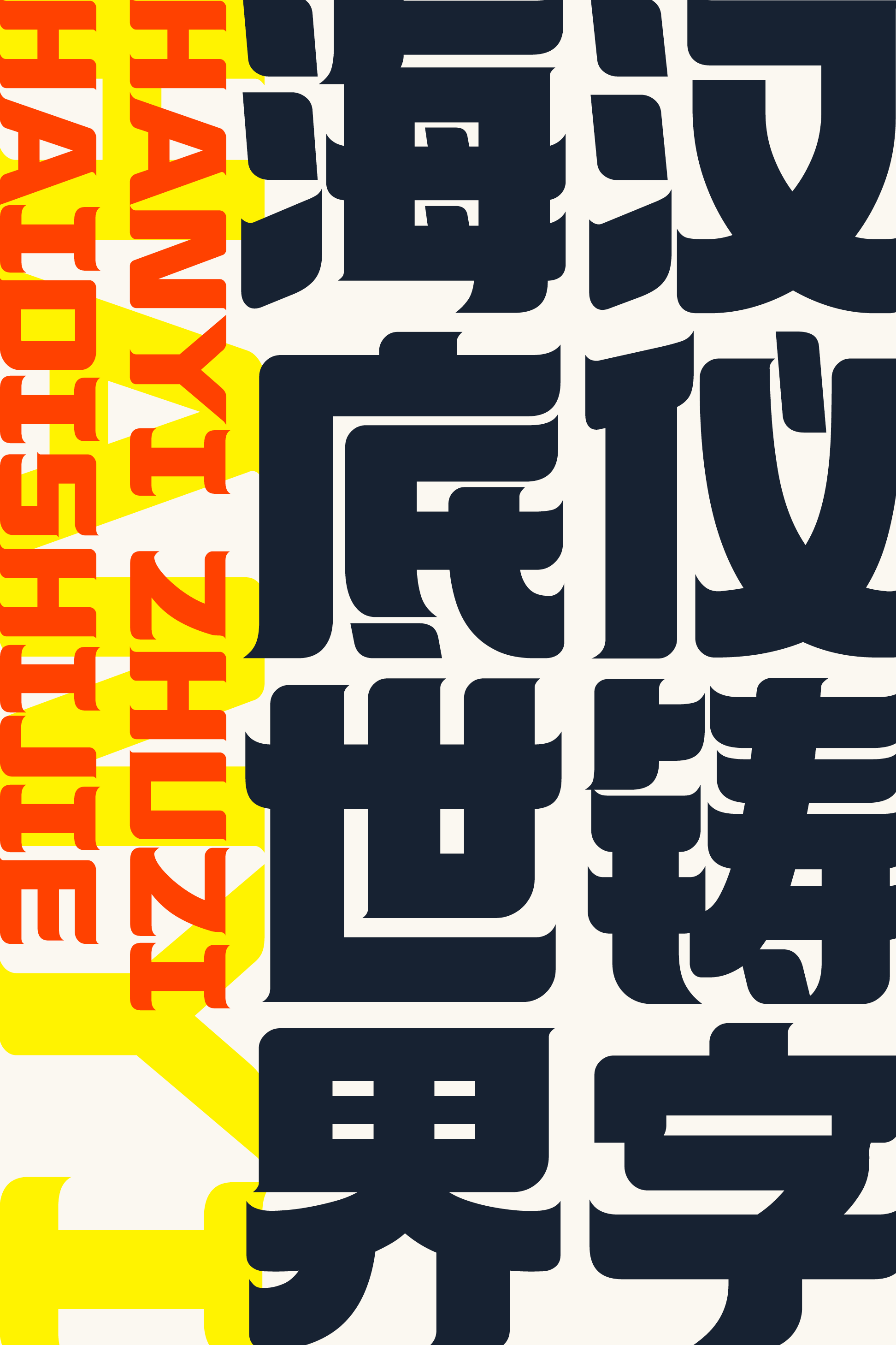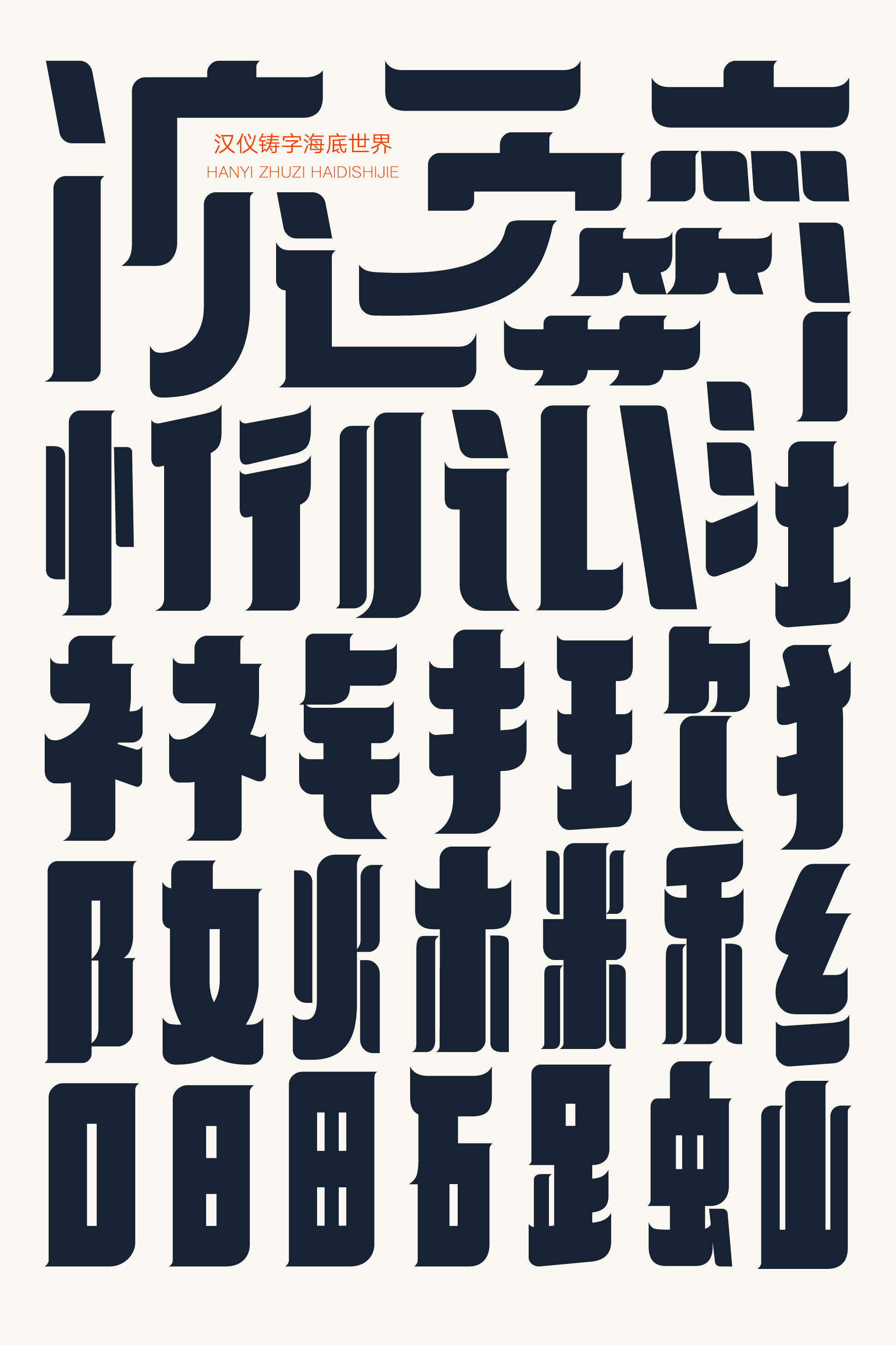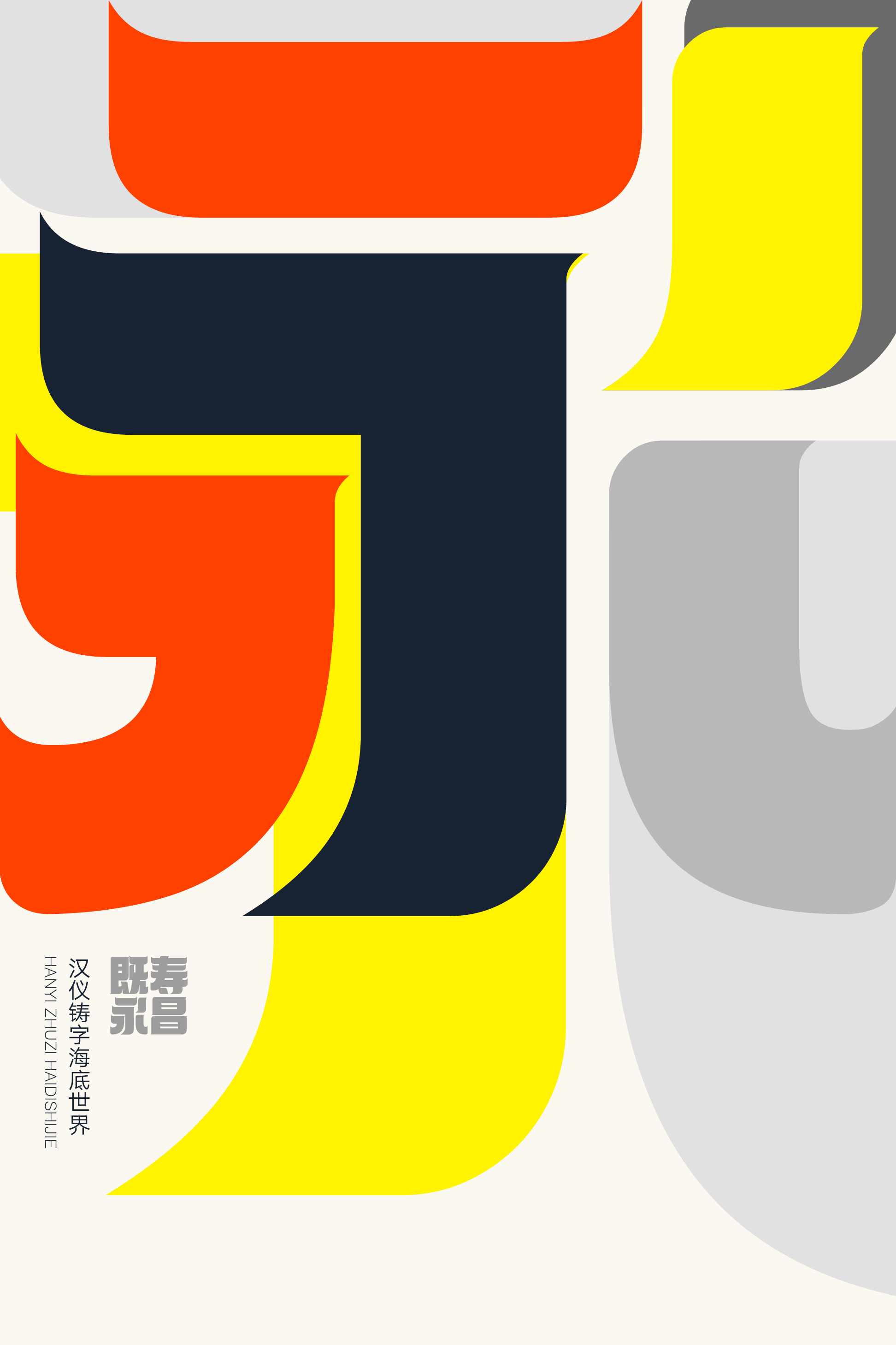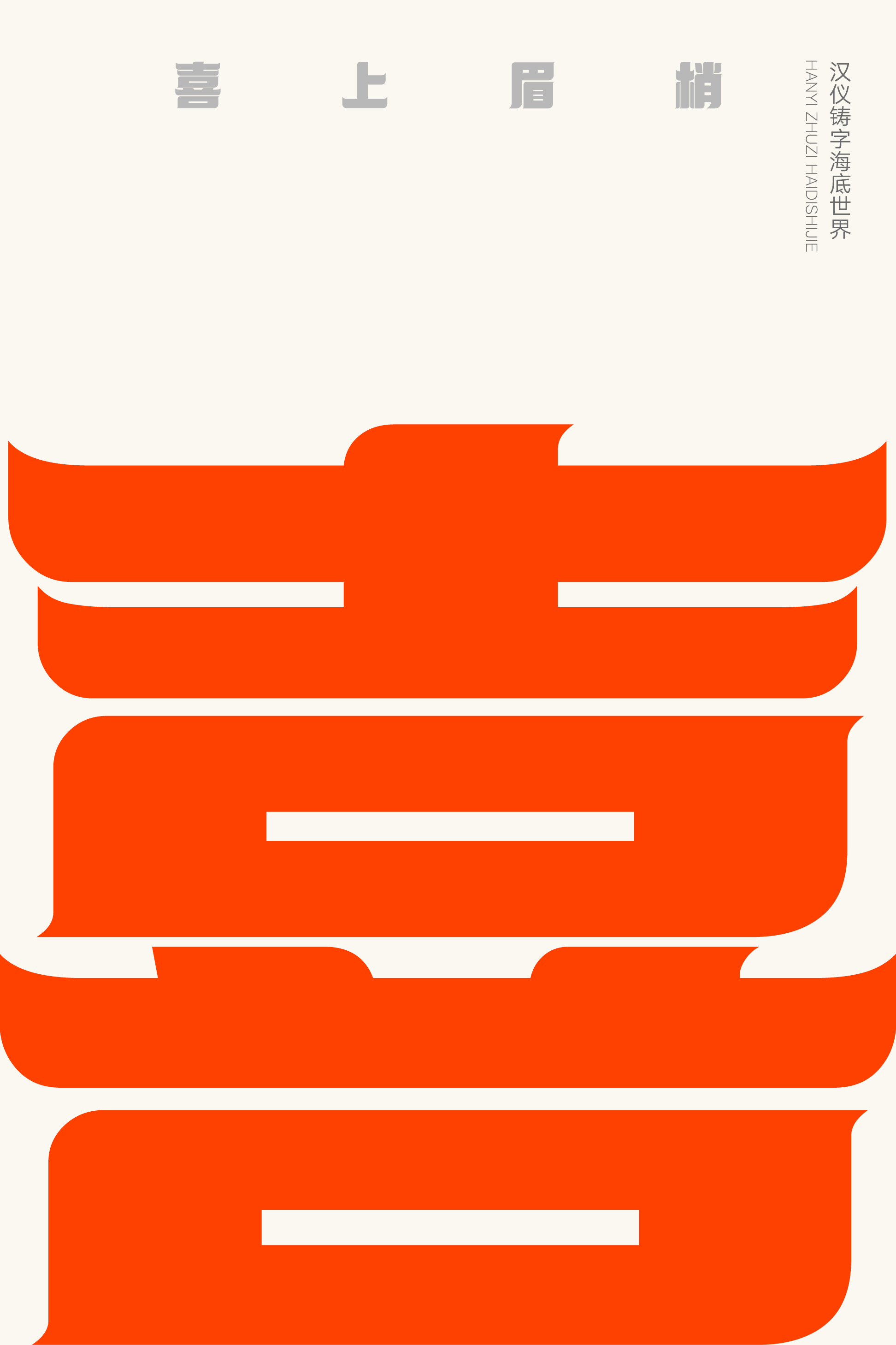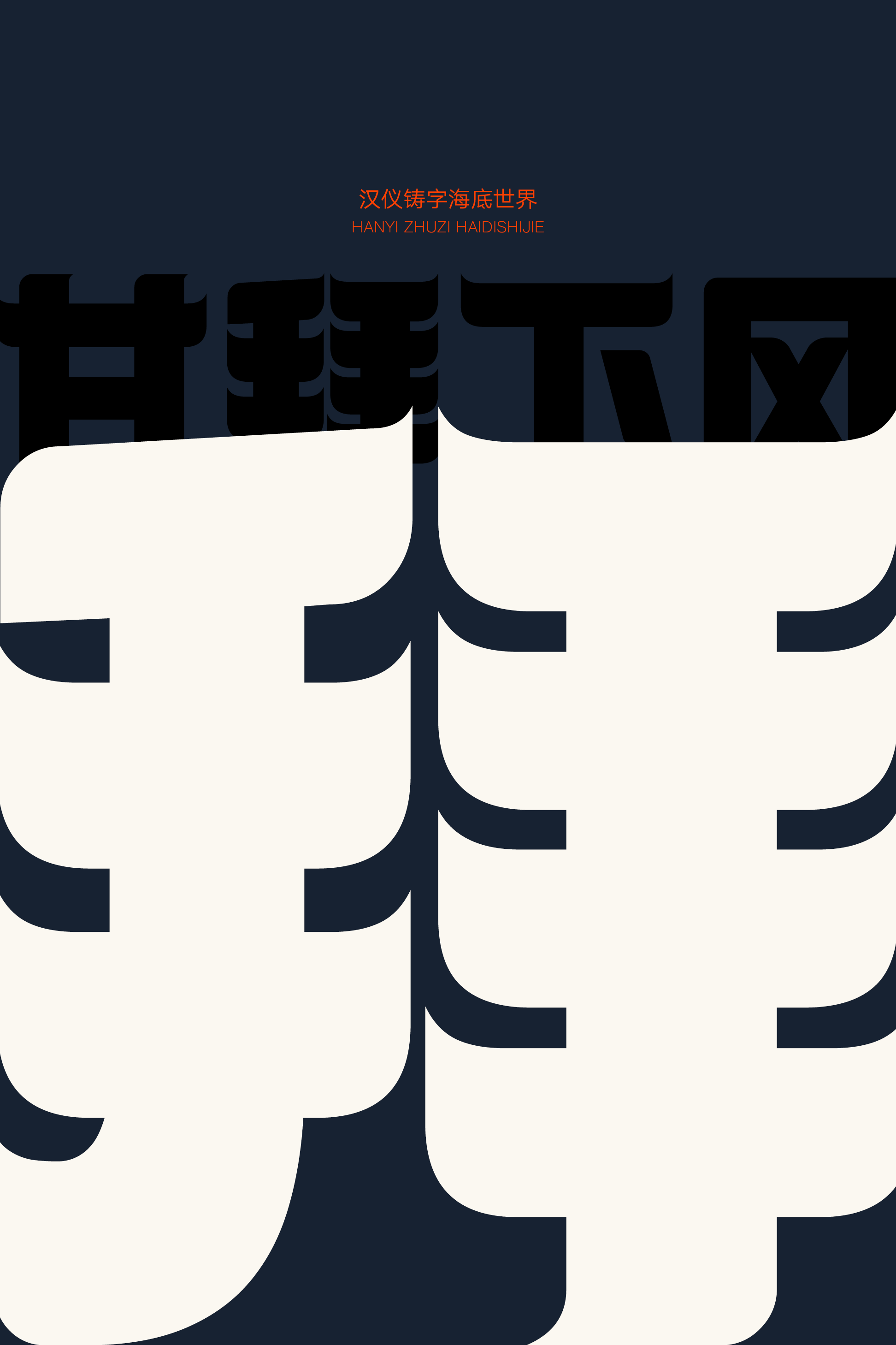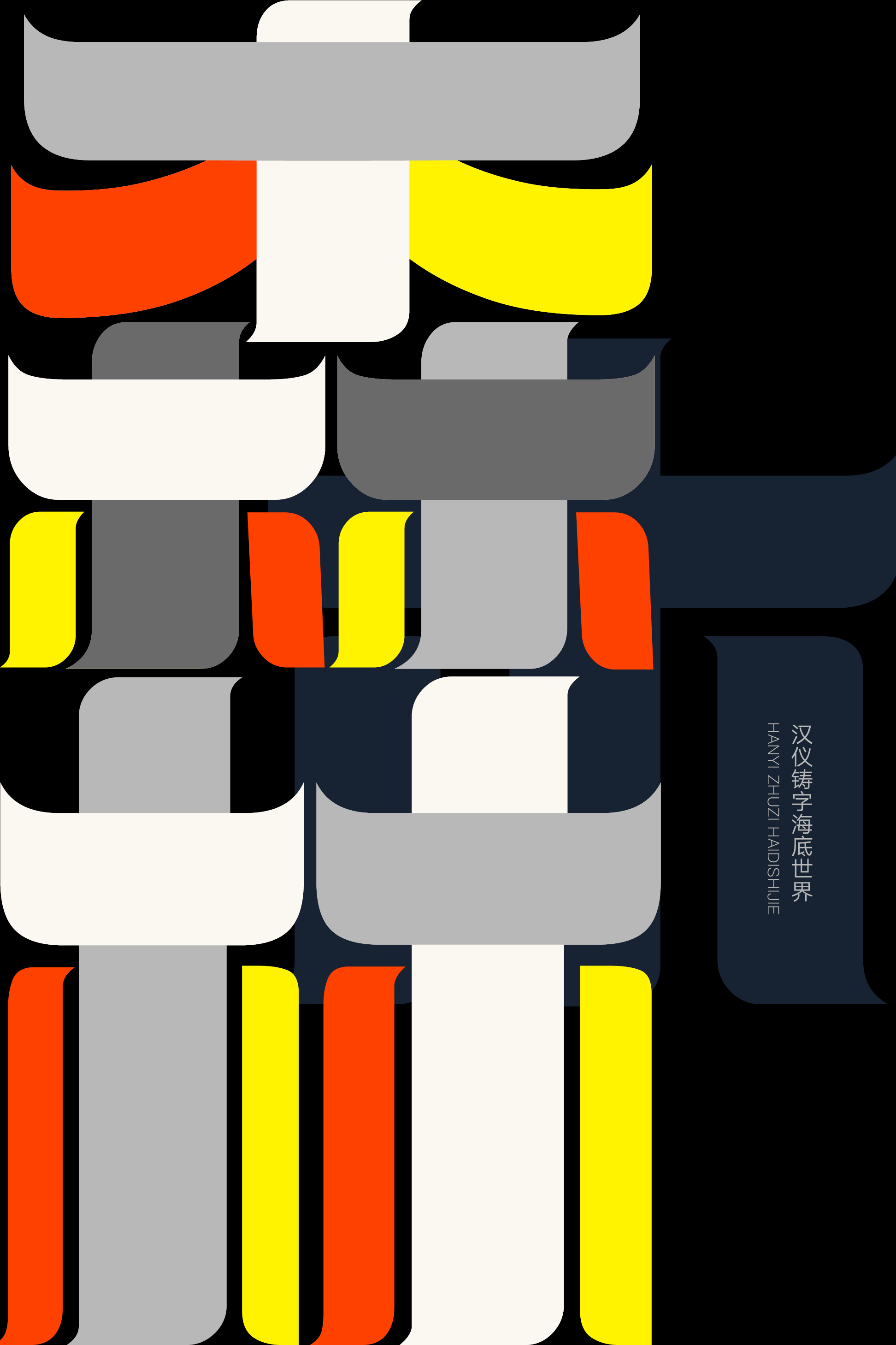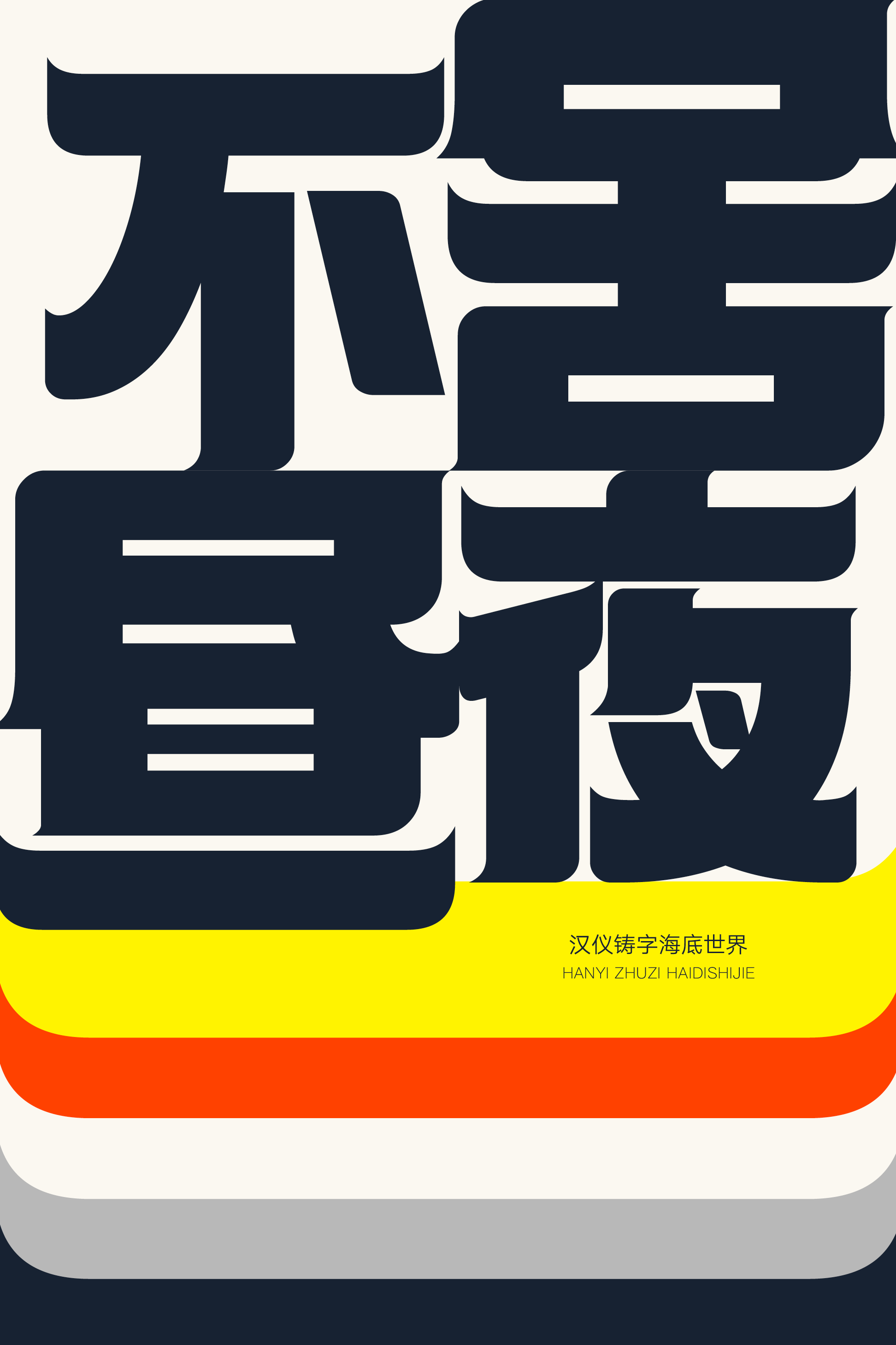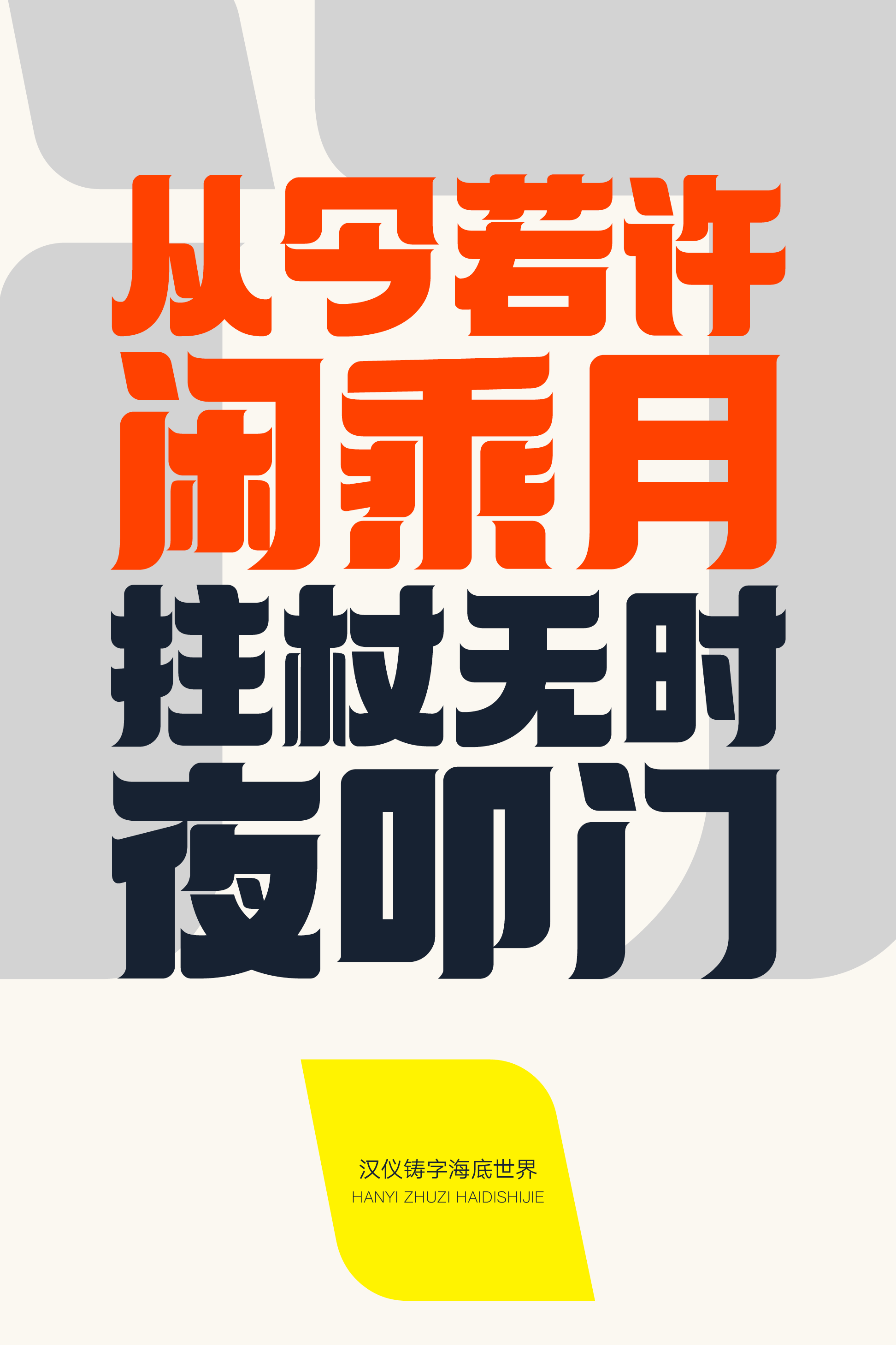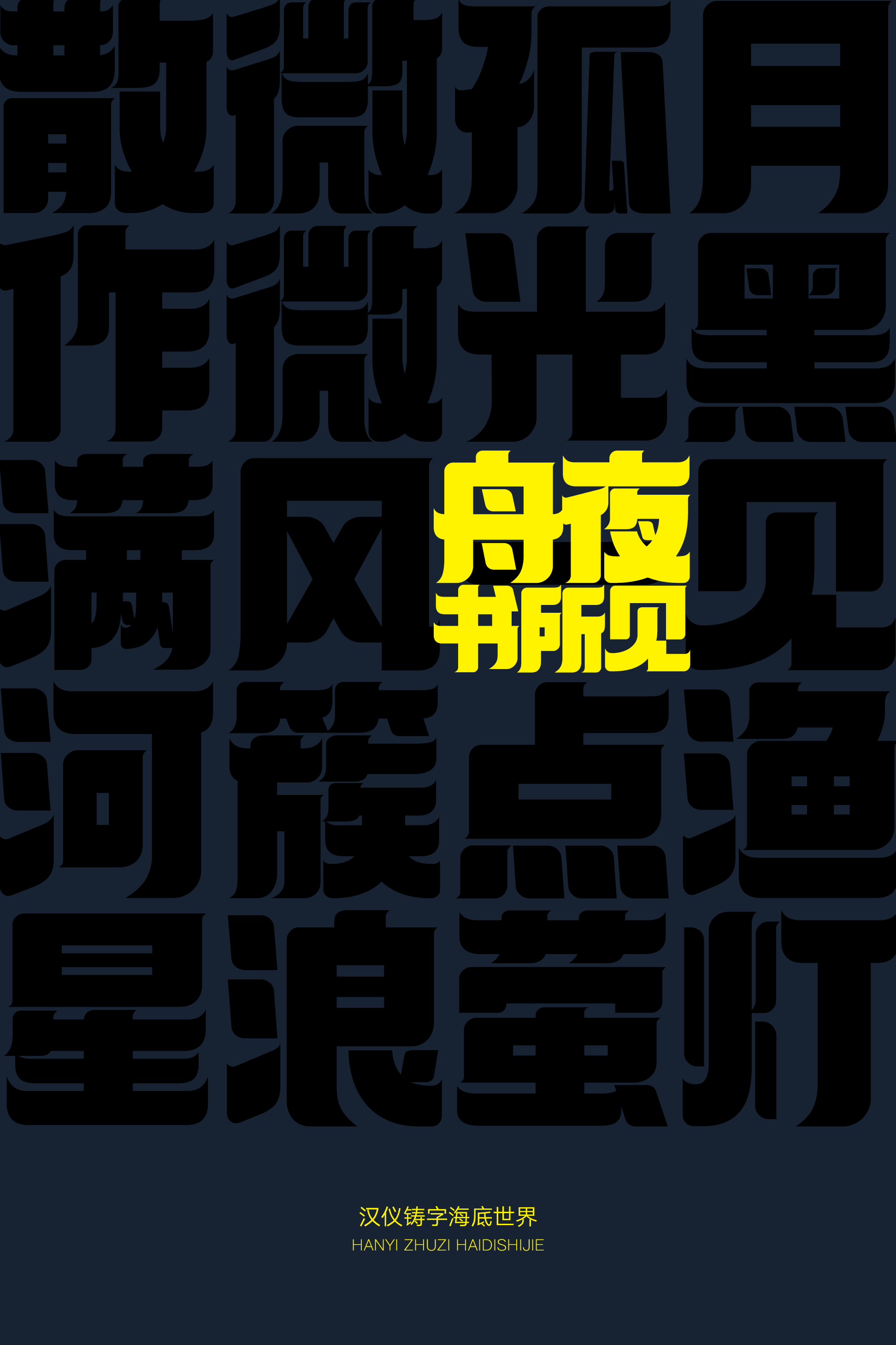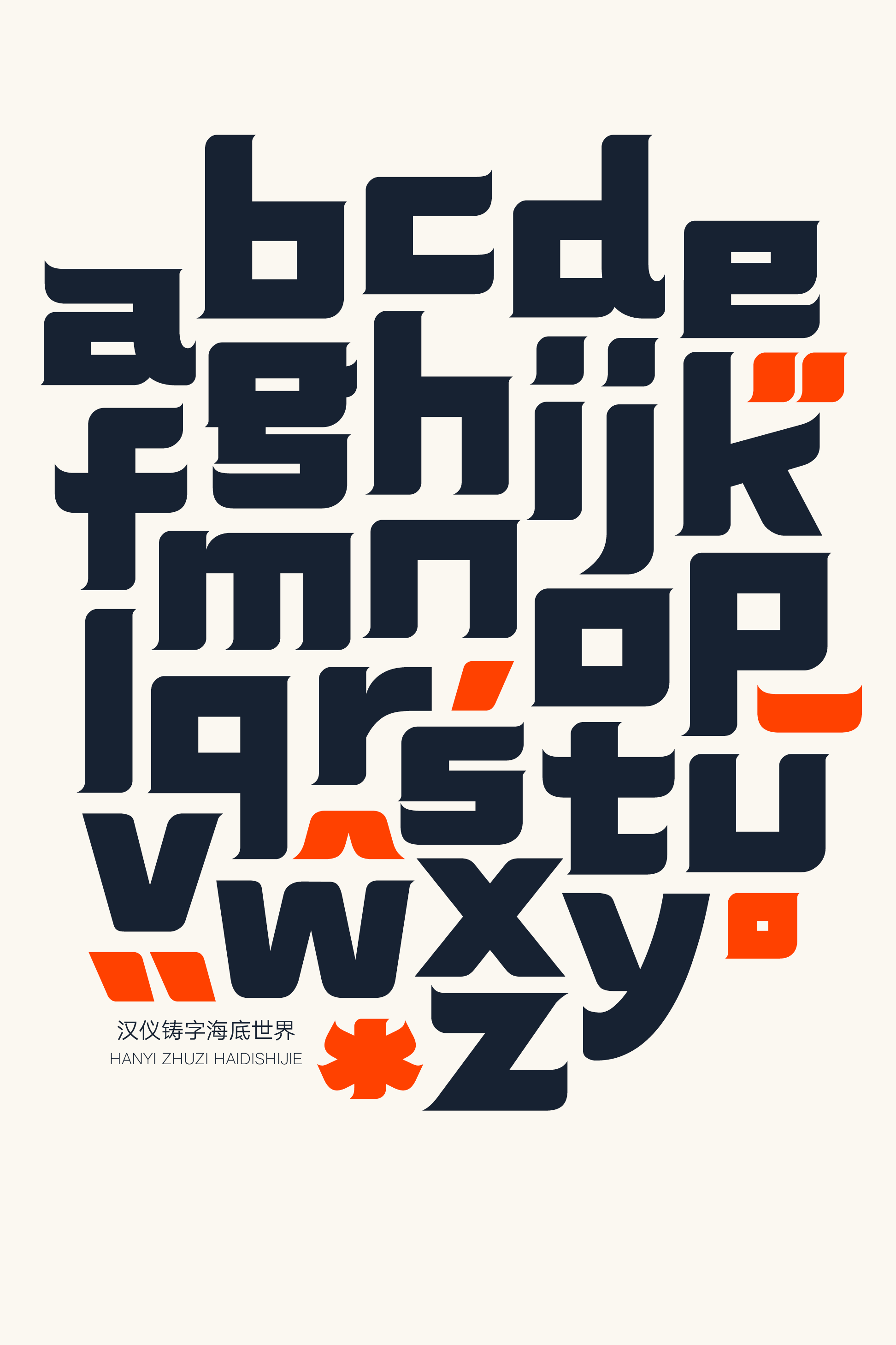
汉仪铸字海底世界
充满未知的海底世界,神秘而深邃…汉仪铸字海底世界以充盈的字形和宽大的笔画打造出海底世界的趣味,暗流化作笔画末端的流线造型。这款字体个性鲜明,快面感强,适合作为醒目的标题字体应用于玩具包装、科普绘本、影视动画等使用场景。汉仪铸字海底世界的奇妙历险,现在开始:
近乎正方的字形饱满充盈,视觉效果深邃如海。
笔画整体造型简约,方直形态与圆弧形态结合。
海底的暗流涌动化作笔画末端的流线造型。
极富巧思的笔画排布增添了奇趣。
汉仪铸字海底世界的西文部分同样是方而满的造型,相同的流线笔画设计使中西文匹配风格一致,渲染海底世界的奇幻。